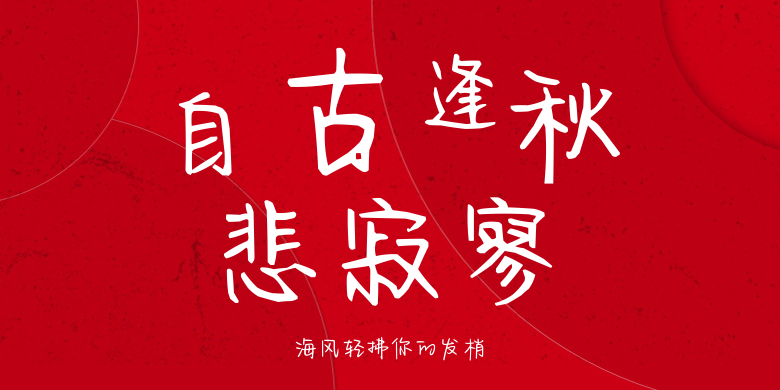
海风轻拂你的发梢
海风轻拂你的发梢,这款字体结构工整、笔画清晰,兼顾美观与易读性,适用于标题、正文、海报、包装、LOGO 等多种场景。字形优雅稳定,风格百搭耐看,适配日常排版与创意设计,让文字呈现更舒适、更具质感。海风轻拂你的发梢一笔一画,皆是细节,以均衡的比例、流畅的线条打造舒适视觉体验,字形端正大气,风格简约现代。无论是商业设计、品牌宣传还是日常排版,都能轻松驾驭,让文字更有格调与力量。海风轻拂你的发梢字体下载。